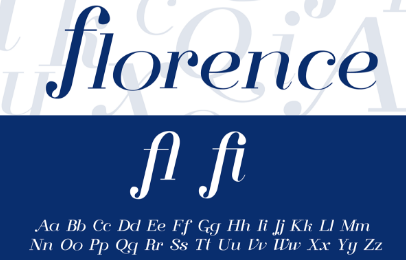
Florence Font
Introduzimos a Florence Font – uma elegante tipografia serifada com linhas modernas e estilo Italic. Criada por Lily Bather, ela é perfeita para design de logomarcas, cartões de visita, layouts de revistas ou anúncios, cabeçalhos em projetos de ilustração em grande escala e mais. Seu caráter minimalista e sofisticado lhe dá um visual profissional que combina bem tanto com elementos formais quanto com designs modernos. Com estilos diferentes para escolha, a Florence Font é uma excelente opção para quem procura um visual elegante sem perder o toque clássico das serifas.